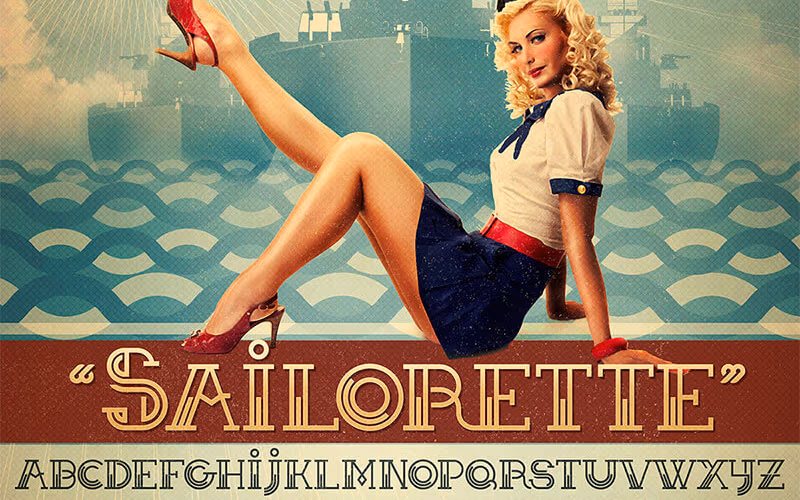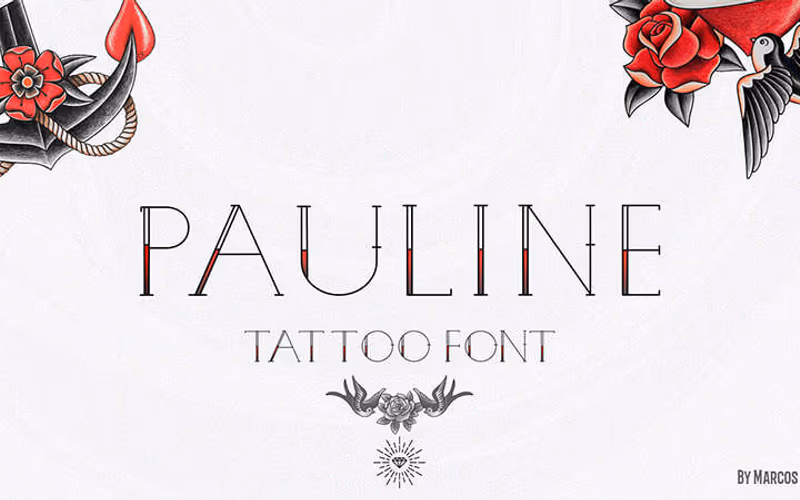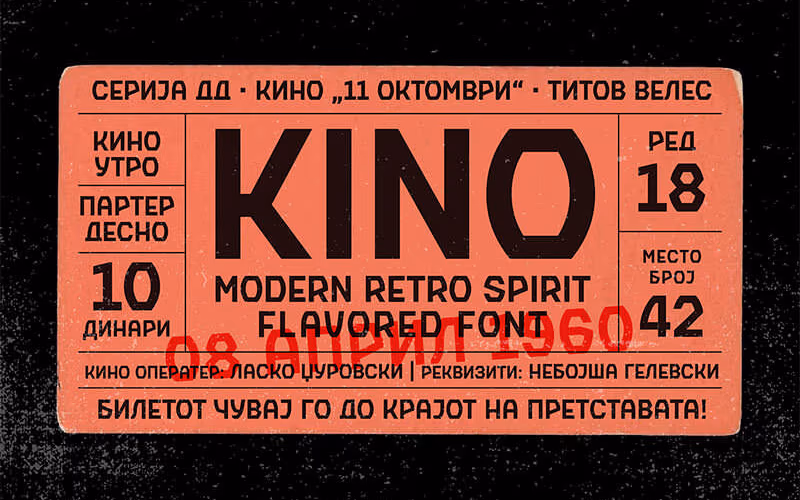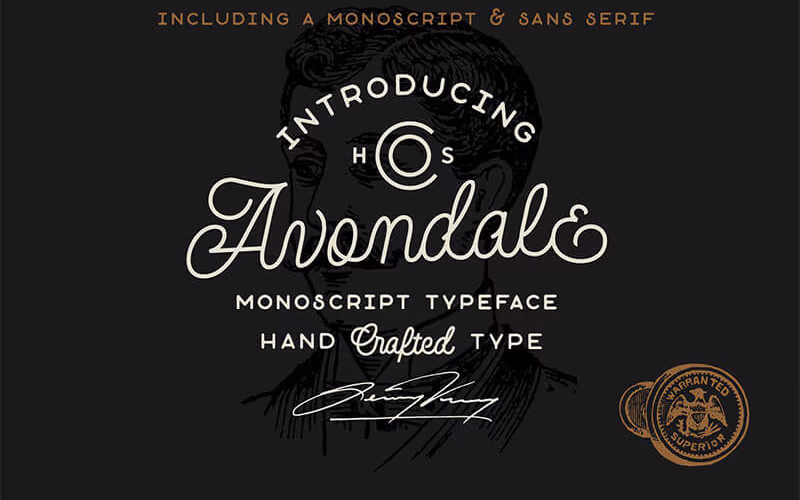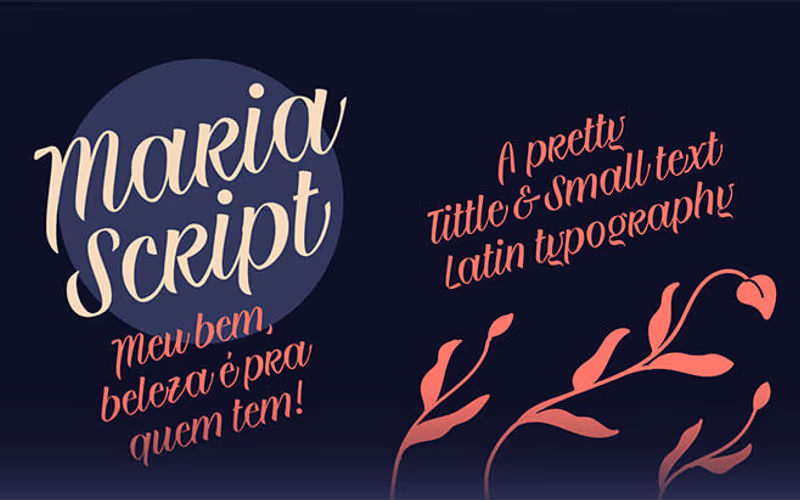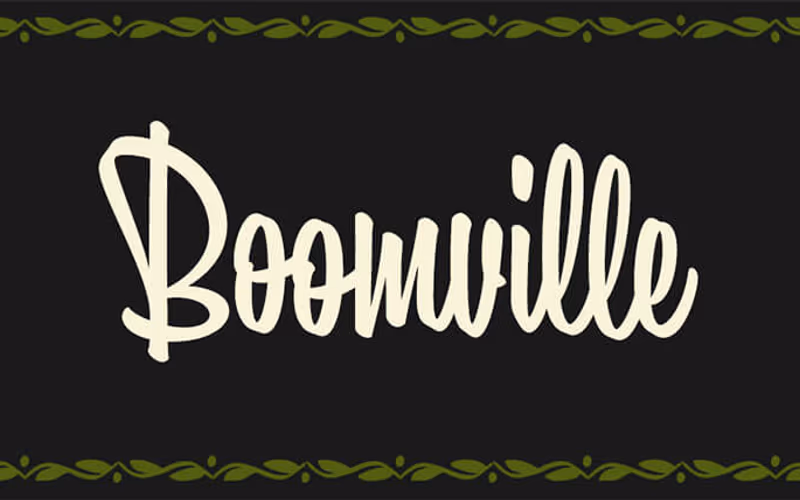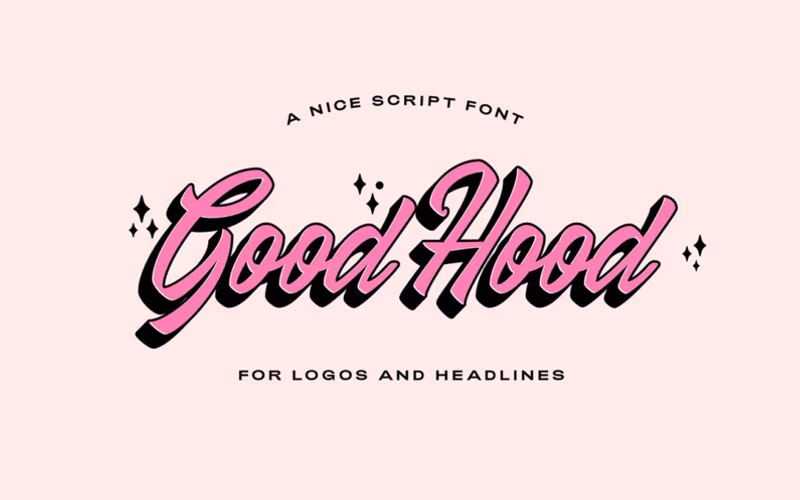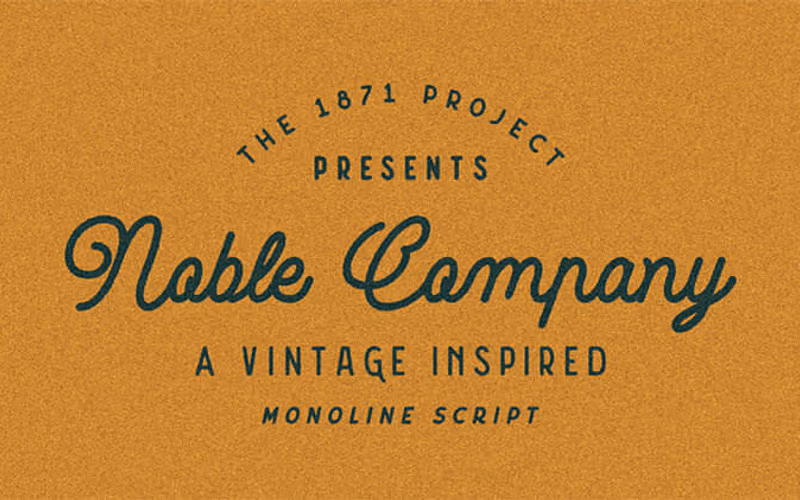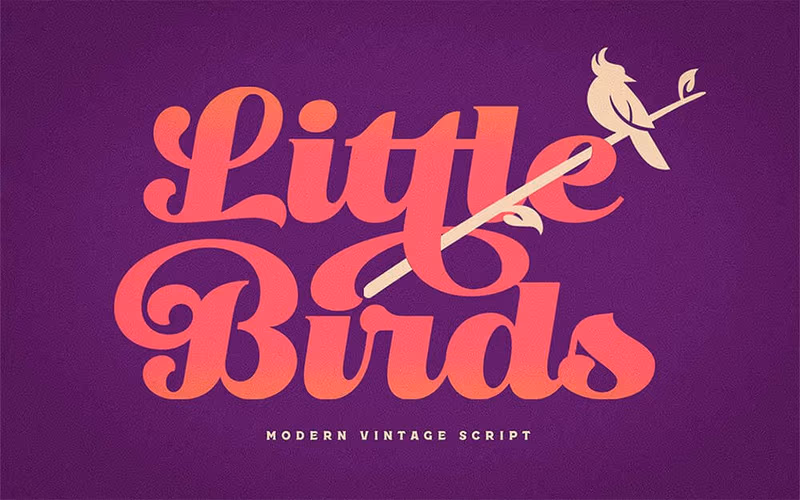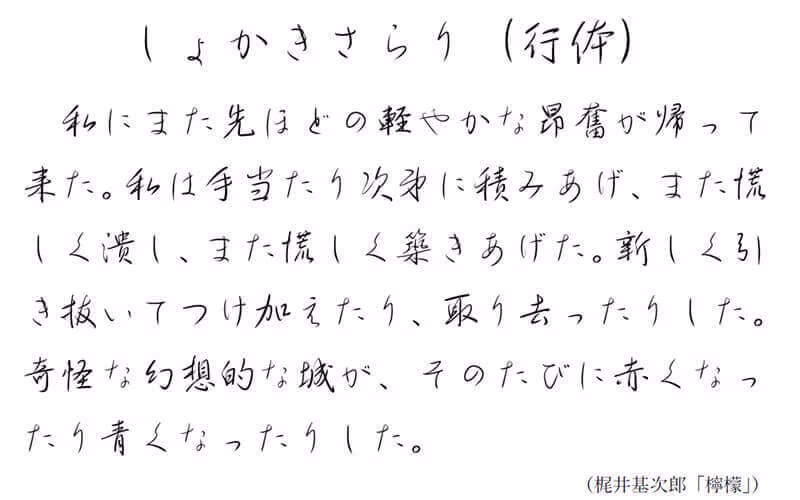
タトゥーデザインにインスパイアされたヴィンテージフォントが魅力。レトロなデザインを演出したいときに使える。個人的にはポスターやロゴに使うと雰囲気が出るかも。文字の装飾が細かいので、小さいサイズでの使用には注意が必要。
アンティークな雰囲気が魅力のPauline Font。クラシックなタトゥーデザインにインスパイアされたフォントで、ヴィンテージ感を演出できる。ポスターやロゴデザインに最適で、個人的にはレトロなプロジェクトにぴったりかも。
ビンテージスタイルの筆記体フォント『Garment District』が魅力。細いモノラインで描かれた文字が特徴で、正直どんなプロジェクトにもクラシカルな雰囲気をプラスできる。大文字アルファベットには2スタイルが用意されていて、カスタマイズが自在なのもポイントなんですよね。
KINO Free Fontは、レトロな雰囲気を醸し出すモダンなスクリプトフォントが魅力。正直、ヴィンテージデザインやポスター制作にぴったりかも。ちなみに、細かいディテールがあるので、大きめの見出しで使うとその良さが際立つ。
Avondale Monoscriptは、モノラインの一筆書きスタイルが魅力。レトロな雰囲気を演出できるので、ビンテージ感を求めるデザインには最適。ちなみに、見出しやロゴに使うと、その独特の味わいが際立つかも。
BEATTINGVILEは、手書き風の美しいブラシフォントが魅力。ブランディングやラベルデザインに活用できる。個人的にはロゴ制作にもピッタリなんですよね。手書き感を出したい人におすすめ。
Maria Scriptは、手書きスタイルをベースにした筆記体フォントが魅力。小さな文字でも可読性を保てるので、名刺や招待状に結構使える。手書き風デザインを求めているならこれがおすすめ。
Boomvilleの縦長スタイル、レトロ感を醸し出す筆記体が魅力。躍動感あるデザインで、タイトルやヘッダーに使うとインパクトが出せる。正直、ビンテージ系プロジェクトには最適かも。
90年代のレトロな看板を彷彿とさせるGood Hood Script Fontが魅力。合字リガチャや代替フォントが揃うので、デザインの幅が広がる。正直、レトロな雰囲気を出したいポスターやTシャツデザインに最適かも。
Noble Companyはビンテージ感漂う筆記体フォントが魅力。これ、地味に便利で、特にロゴや招待状での使用に最適。個人的には、背景をシンプルにしてフォントを際立たせると効果的かも。
Rampage Scriptは、レトロな筆記体にザラッとしたテクスチャが魅力。ヴィンテージ感を演出できるフォントで、個人的にはポスターやロゴデザインに最適。ちなみに、背景をシンプルにすると文字が引き立つかも。
Little Birdは、ヴィンテージ感漂うスクリプトフォントが魅力。レトロなデザインや手書き風のプロジェクトに最適。個人的には、招待状やポスターに使うと雰囲気が一気にアップするかも。ちなみに、細かいディテールが多いので、印刷時には解像度に注意が必要。
すらすら流れる筆致が魅力の日本語フォント、しょかきさらり。JIS第一水準まで対応してるから、結構いろんな場面で使える。和風デザインや落ち着いた雰囲気を出したいときにおすすめ。
鉛筆の懐かしさを感じさせるフォント、砧 芯・鉛筆 Italic StdNが魅力。オーソドックスな書き味で、読みやすさが際立つ。手書き風のデザインを求めるならこれが最適。正直、このフォントでノスタルジックな雰囲気を演出するのが面白いかも。
Turquoise Kimono Fontは、流れるようなストロークと遊び心あるループが魅力。手書きっぽさが際立つこのフォント、正直、招待状やポスターなんかに使うと一気にオシャレ度アップできる。エレガントなデザインを求めるならこれがおすすめ。
UT Lights Innは、レトロ感たっぷりのスクリプトフォントが魅力。ヴィンテージデザインを作りたいときに結構使える。ちなみに、ポスターやロゴに使うと印象がグッと引き締まるかも。
流れるような筆跡が魅力のThreads Clube。エレガントでありながら、温かみを感じさせるスクリプトフォントなんですよね。手書き風のデザインを求めるならこれが最適。正直、招待状やラグジュアリーなブランドロゴにぴったりかも。
Tirelessly Love You Fontは、サラサラと流れるような筆記体が魅力。結婚式の招待状やロマンチックなプロジェクトに最適。ちなみに、背景とのコントラストをしっかり取るとこのフォントの美しさが際立つかも。
大文字のスワッシュが特に印象的なBaliana Fontが魅力。高級感とレトロっぽさを同時に演出できる、結構使えるフォントです。ヴィンテージデザインやロゴ制作に最適。
手描き感がそのまま生きているモダンなサンスクリプトフォントが魅力。ポスターやカードデザインに使うと、温かみのある雰囲気が演出できる。正直、手書き風を求めているならこれが最適かも。ちなみに、細かいディテールがあるので大きめに使うとより映える。
クラシックで洗練された印象を与えるLuthier Free Fontが魅力。個人的には、エディトリアルデザインや高級感を出したいプロジェクトに最適。ちなみに、細かいディテールが光るので、大きめの見出しで使うと効果的かも。
高級感たっぷりのQene-G Serif & Signature Scriptが魅力。セリフと筆記体の組み合わせで、ナチュラルなラグジュアリー感を演出できる。ブランドロゴや高級商品のパッケージデザインに最適。正直、洗練された雰囲気を出したいときにこれが面白い。
Kotori Roseは、優雅でフェミニンなフォントが魅力。手書き風のエレガントなスタイルで、結婚式の招待状やロゴデザインに最適。個人的には、背景をシンプルにしてフォントを主役にする使い方が面白い。
Waywardは手描き感が魅力のフォントで、特に筆記体やスクリプト書体と組み合わせると映えるデザイン。正直、ナチュラルで温かみのある雰囲気を出したいときにはこれが最適。ロゴや招待状に使うと、地味におしゃれ度がアップするかも。
細いモノラインで描かれたビンテージスタイルの筆記体が魅力。大文字アルファベットに2スタイルが用意されているから、カスタマイズも自在にできる。個人的には、レトロな雰囲気を演出したいプロジェクトに最適かも。ちなみに、細かい調整が必要な場合は、アウトライン化して微調整するのがポイント。